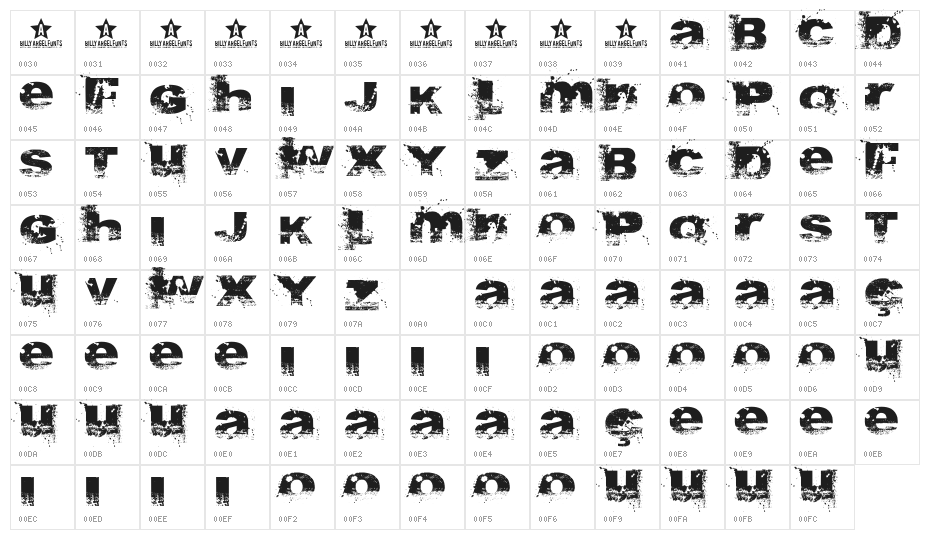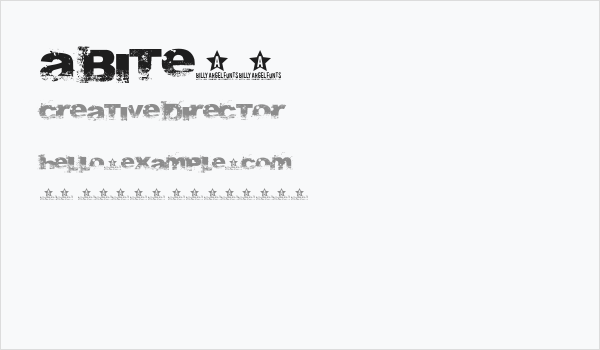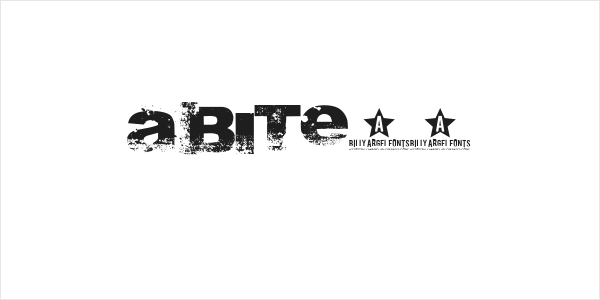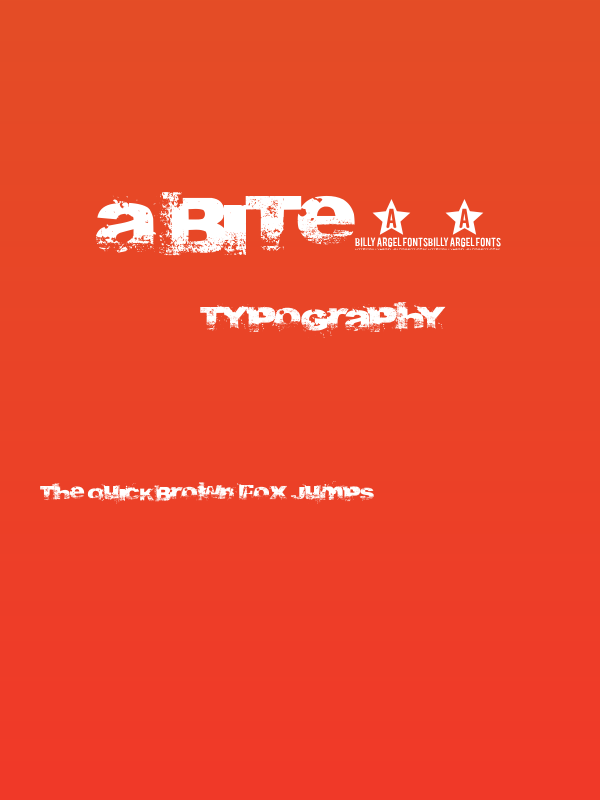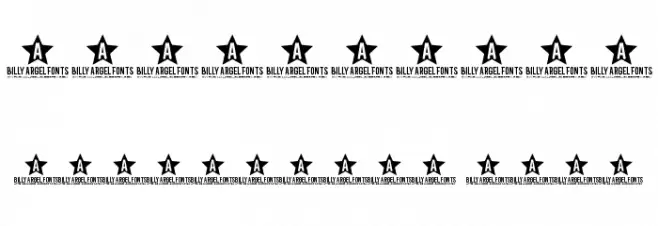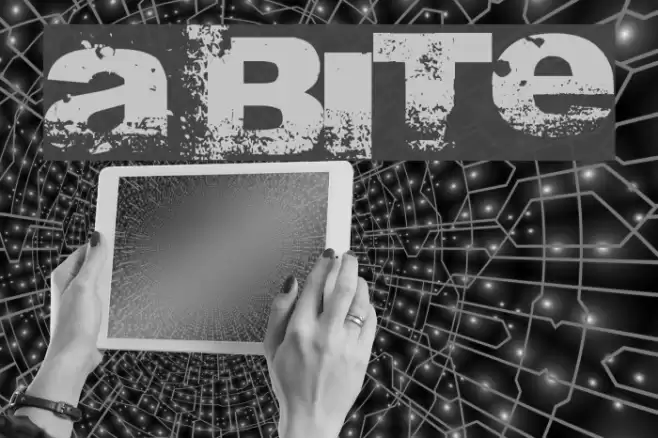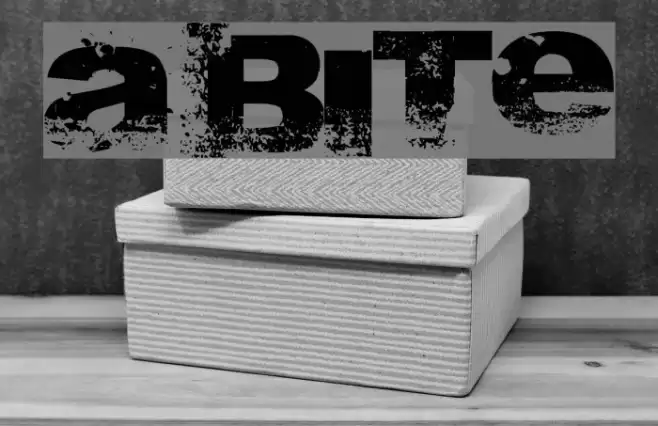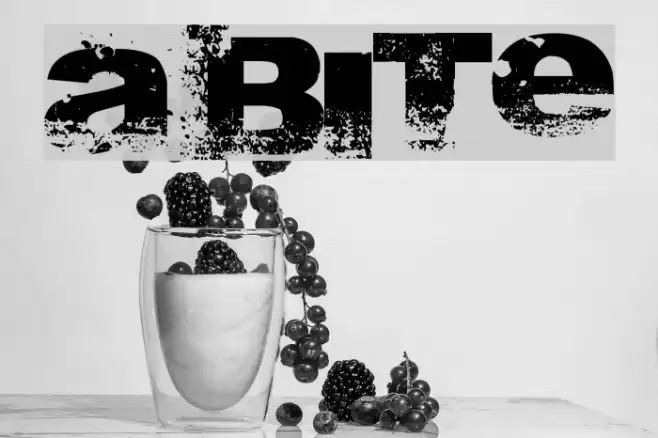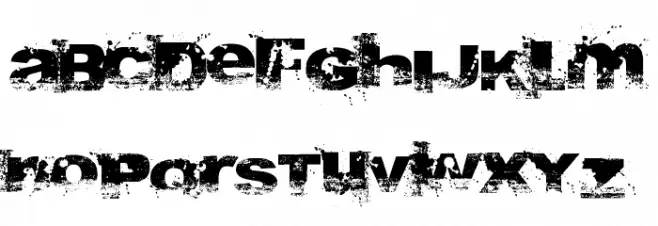
A bite__ Font
✎ Distorted Eroded
| श्रेणियाँ | Distorted Eroded |
| समग्र शैली | Grunge, Urban, Edgy |
| उपयोग का मामला | Headlines, Logos, Posters |
| सुझाए गए प्रोजेक्ट | Ideal for album covers, posters, streetwear branding, and urban-themed designs. |